Создавая страницу цифрового альбома для вырезок, легко влюбиться в красивые, замысловатые шрифты и яркие цветовые палитры. Мы часами выбираем идеальную бумагу и элементы! Но затем наступает момент добавить текст, журнал и заголовок.
Внезапно мы спрашиваем: почему мой текст теряется? Почему мой дневник выглядит беспорядочным?
Выбор типографики и цвета — такая же часть творческого процесса, как выбор бумаги и украшений. Чтобы помочь вам создавать страницы, которые выглядят потрясающе и легко читаются, давайте рассмотрим пять простых правил дизайна текста для цифрового скрапбукинга.
Не весь текст выполняет одинаковую функцию
Прежде чем выбрать шрифт, спросите себя: что этот текст делает на моей странице?
Заголовки и Word Art: Их работа — привлечь внимание, создать настроение и привлечь внимание. Поскольку заголовки обычно состоят всего из нескольких слов, они могут использовать жирные, эффектные или супердекоративные шрифты.
Ведение дневника: Его задача — передать воспоминания. Журналирование состоит из полных предложений и абзацев. Для ведения журнала читаемость становится гораздо более важной. Декоративные шрифты, которые выглядят потрясающе как заголовок из двух слов, быстро вызовут утомление глаз, если растянуть их на четыре строки журнала.
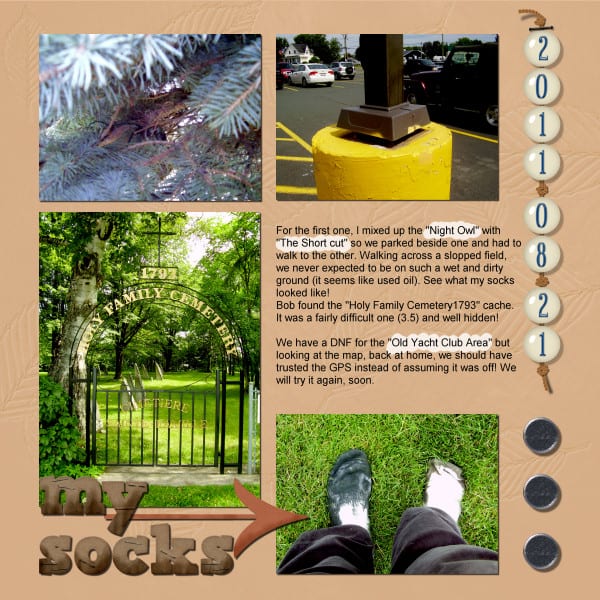
Эмпирическое правило: Оставьте свои причудливые, насыщенные шрифты для заголовков и пусть в вашем дневнике останутся чистые, легко читаемые шрифты.
Сопоставьте шрифт с целью
При просмотре библиотеки шрифтов (или альфа-хранилища) полезно классифицировать их по визуальному весу и стилю:
Декоративные и отображаемые шрифты: Необычные, состаренные, тематические или сильно украшенные шрифты. Отлично подходит для титулов!
Сценарии и каллиграфия: Элегантные и игривые, но сложные циклы и жесткий кернинг могут затруднить чтение длинных блоков текста.
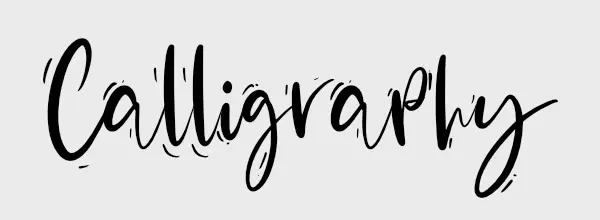
Простые шрифты с засечками и без засечек: Чистые, классические и надежные. Это ваши лучшие друзья для ведения дневника.
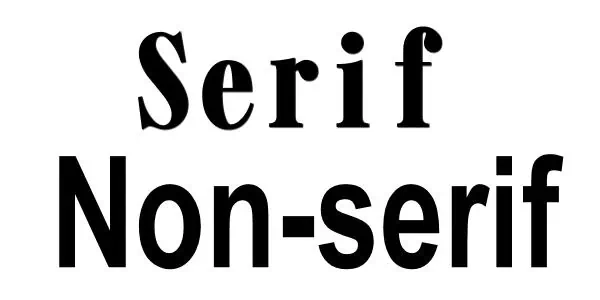
Сжатый и жирный/жирный: Крупные шрифты сразу привлекают внимание, а сжатые шрифты экономят место. Только следите за тем, чтобы сжатые буквы не были сжаты настолько сильно, что не расплывались вместе.
Золотое правило: Чем больше у вас текста, тем проще должен быть ваш шрифт.
Разница в цвете — это еще не вся история
Соблазнительно сопоставить цвет шрифта непосредственно с оттенком бумаги с рисунком. Но здесь скрыта ловушка: два совершенно разных цвета могут иметь очень похожую яркость. Они могут казаться совершенно разными из-за разных оттенков. Этого может быть вполне достаточно для большого и жирного текста. Однако одной этой цветовой разницы может быть недостаточно, если текст меньше, тоньше или использует более сложный шрифт.
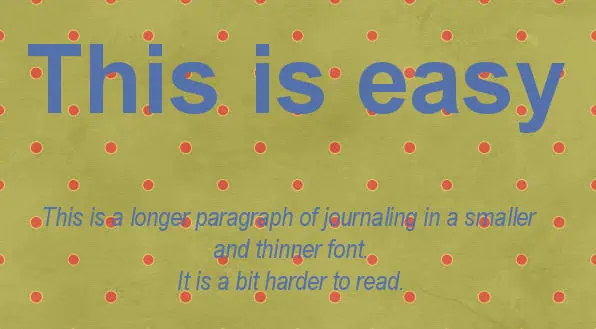
Преобразование изображения в оттенки серого устраняет разницу в оттенках. Если текст внезапно исчезает на заднем плане, вы знаете, что большая часть его видимости обусловлена разницей в цвете, а не разницей в яркости.
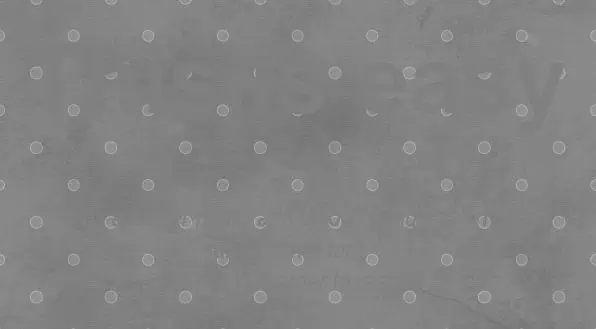
Если текст исчезает в оттенках серого, но легко читается в цвете, возможно, вам не нужно ничего менять, особенно если заголовок большой и жирный. Но для небольшого, тонкого, декоративного или важного текста увеличение разницы в светлоте может облегчить чтение.
И «тест» в оттенках серого согласуется.
Итак, если вам нравится выбранный вами цвет текста, но он недостаточно выделяется, вам не обязательно выбирать другой цвет. Попробуйте сделать тот же цвет светлее или темнее.
Тёмное на светлом или светлое на тёмном?
И темный текст на светлом фоне, и светлый текст на темном фоне могут обеспечить отличный контраст. Однако небольшие или изящные светлые буквы иногда труднее читать на темном фоне. Если вы хотите использовать эту комбинацию, может помочь увеличение размера или веса шрифта.
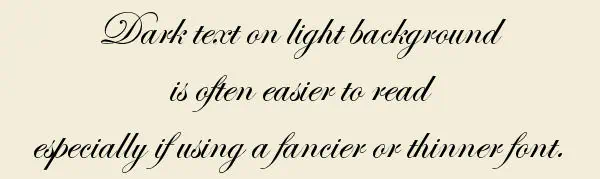
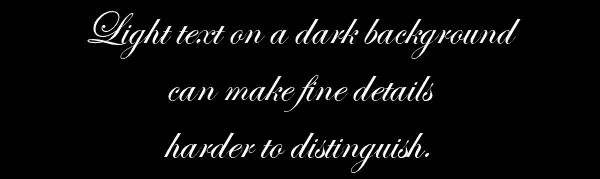
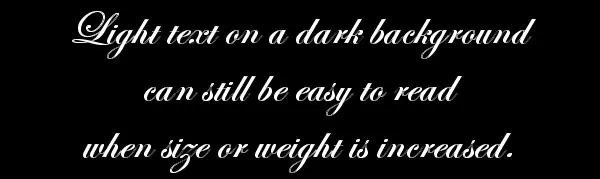
В этих примерах используется простой фон, на котором тексту больше не с чем конкурировать. Добавьте узор или текстуру, и выбор шрифта, размера, насыщенности и контрастности станет еще более важным.
Посмотрите, что скрывается за вашим текстом
Даже если цвет вашего текста резко контрастирует с цветом бумаги, узоры и текстуры конкурируют с текстом.
Оживленный фон: Яркий цветочный принт, густая акварельная текстура или рисунок потрепанного дерева создают визуальный шум. Декоративные шрифты, размещенные поверх них, могут быстро стать трудными для чтения.
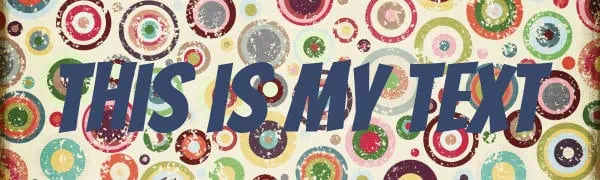
Однотонный или тонкий фон: Мягкие твердые тела, легкие текстуры или низкоконтрастные узоры придают тексту больше пространства.
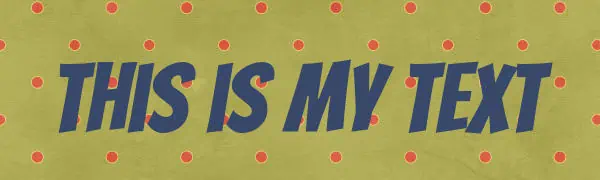
Посмотрите, как эти варианты работают вместе
Необычный шрифт заголовка + простой/тонкий фон: часто хорошая комбинация, потому что она придает декоративному шрифту больше пространства.!
Необычный журнальный шрифт + простой/тонкий фон: это может быть сложная комбинация, на которую также будут влиять длина текста и общий размер шрифта.
Готовы попробовать это в своем следующем макете?
В следующий раз, когда вы запустите программу для цифрового скрапбукинга, найдите минутку, чтобы взглянуть на свой текст через эти разные линзы. Сбалансировав выбор шрифта, контрастность, размер и фон, вы можете быть уверены, что ваш текст дополняет ваш дизайн, не заставляя читателя работать слишком усердно.